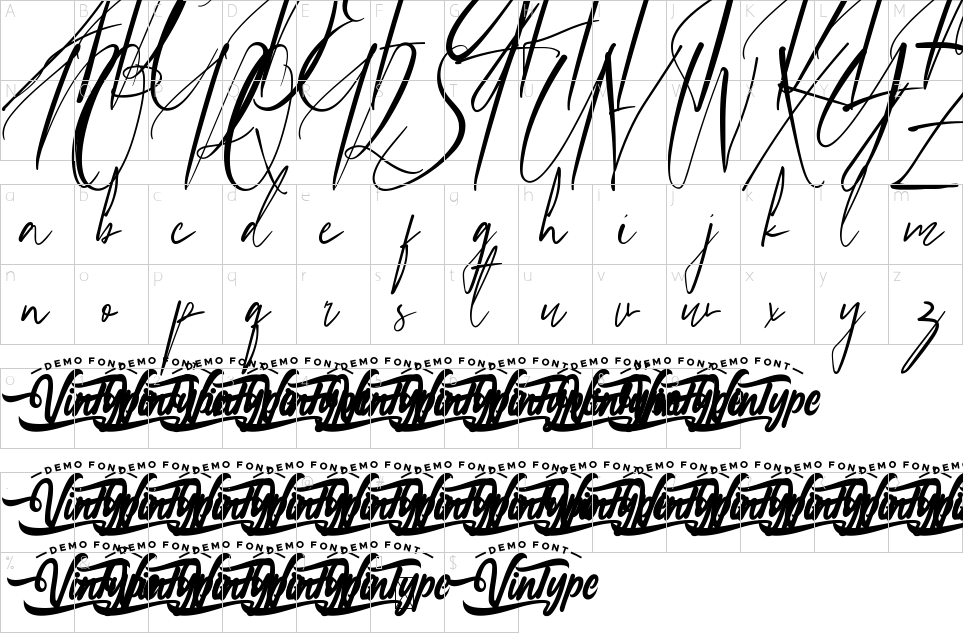
Manda Stephanie Font | 1001 Free Fonts – Download Grátis
Descubra a beleza única da fonte Manda Stephanie no catálogo de fontes grátis da 1001 Free Fonts. Manda Stephanie foi criada por VinType e já foi baixada por 2.240 pessoas. Esta fonte é uma excelente escolha para designers e criadores de conteúdo que buscam uma fonte que combine elegância com modernidade. Com uma aparência fluida e uma personalidade única, Manda Stephanie oferece uma opção de estilo elegante para textos e gráficos. Este é mais um exemplo da vasta gama de opções gratuitas disponíveis na 1001 Free Fonts, permitindo a todos o acesso a uma variedade de recursos de design gráfico. Baixe Manda Stephanie para Windows e Mac e descubra como esta fonte pode dar um toque especial a seus projetos.